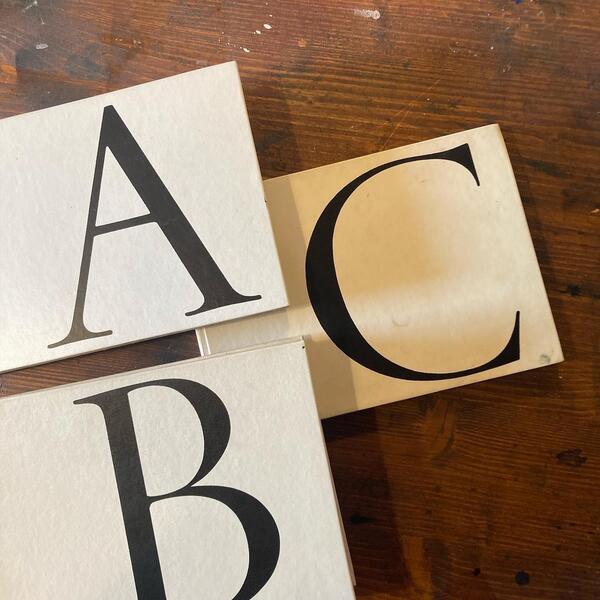
»ABC of Lettering and Printing types« ist ein umfangreiches, dreiteiliges Werk des schwedischen Designers und Kalligrafen Erik Lindegren. Die Einzelbände beschäftigen sich mit den Themen Lettering (im weitesten Sinne, also auch Kalligrafie und zeichnerisches Gestalten mit Schrift), Printing Types (Druckschriften) und Schriftgeschichte.
Band A – Lettering:
Im ersten Band werden schriftkünstlerische Arbeiten vorgestellt, angefangen bei bei Aufbau und Form römischer Inschriften bis zu seinerzeit zeitgemäßen Schriften im angewandten Bereich wie Logos und Buchcover. Die 133 Seiten sind voll mit teils mehrfarbigen Abbildungen von Arbeiten internationaler Künstler – einiges auch von Hermann Zapf – und vom Autoren selber.
Band B – Printing Types:
Der zweite Band ist mehr oder weniger ein Schriftmusterbuch für Druckschriften in 333 Seiten. Im Vorwort werden auch verschiedene Ansätze zur Klassifizierung vorgestellt. Die Auswahl der Schriften scheint etwas zusammengesucht, es werden aber viele Schriften mit handschriftlichen Charakter und Zierschriften vorgestellt, aber auch Klassiker ihrer Art.
Band C – An Historical Survey:
Der geschichtliche Überblick zeigt die Entwicklung der lateinischen Schriften in Form und Technik. Auf Grund der Seitenzahl lässt sich schon schließen, dass es die Geschichte nicht besonders umfangreich darstellt. Ein Fokus liegt auch in den historischen Persönlichkeiten, die hier vorgestellt werden (wie Bodoni, Morris, Zapf etc.). Die 135 Seiten sind aber auch ausgiebig und mehrfarbig bebildert.
Zusammenfassung:
Als deutsche/westeuropäische Designer:innen haben wir naturgemäß oft die deutschen Bücher auf dem Schirm, Bücher aus dem englischsprachigen Raum oder den Niederlanden sieht man hin und wieder auch noch – von skandinavischen Gestaltern und Kalligrafen hört man allerdings recht wenig. Und so hat es mich sehr überrascht als ich dieses Buch als Empfehlung aus einem Workshop mit dem norwegischen Kalligrafen Christopher Haanes mitgenommen habe. Dieses Buch lohnt sich für alle, die sich für Kalligrafie und Lettering interessieren, historische Einblicke haben wollen oder Inspiration suchen. Schriftbeispiele für Druckschriften gibt es sicherlich umfangreichere Sammlungen. Auch wenn der zweite Band hier seinen Fokus drauflegt, ist es bestimmt kein Standardwerk zu diesem Thema.
Autor(en): Erik Lindegren
veröffentlicht: 1965
Verlag: Erik Lindegren Grafisk studio
Sprache: englisch
Seiten: Zusammen 623